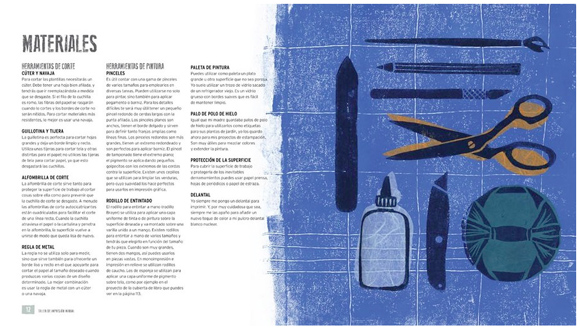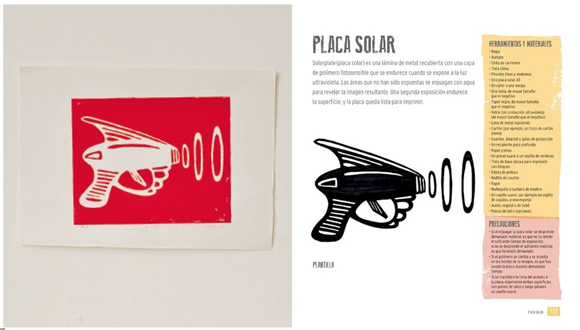
El resurgumiento de la impresión clásica con tipos de plomo o madera (letterpress) es algo que de un tiempo a esta parte hemos podido constatar todos los que nos dedicamos al campo de la comunicación. Muchos clientes piden volver a esta técnica de impresión que devuelve una especie de diseño táctil e imperfecto. Esta técnica de imprimir utilizando figuras en relieve es básicamente sencilla y asumible y no hace falta disponer de grandes medios para experimentar con ella. Asimismo otras técnicas como la serigrafía, o el estarcido también nos pueden proporcionar grandes resultados con una mínima inversión. Es aqui donde el libro Taller de impresión manual. Técnicas, herramientas y proyectos para hacer en casa, nos puede servir perfectamente de guía para comprender que es, como se puede hacer y que podemos conseguir a nivel casero poniendo en práctica los recursos de estas técnicas convertidas en este caso en artesanía.
A través de 23 proyectos entre los que se incluyen la impresión de camisetas, espejos, tarjetas de felicitación o incluso manteles, examinaremos las diferentes técnicas de impresión con todo lujo de detalles, desde las herramientas necesarias hasta los pasos que se han de dar para finalizar el producto. Todos los proyectos son sumamente atractivos y desprenden un acercamiento a una expresión artística muy interesante. Tengo la sensación de que este libro puede proporcionar unas buenas ideas a todo aquel que se quiera introducir en el mundo de la reproducción de imágenes de una forma asequible, creativa y muy divertida.
Taller de impresión manual
Técnicas, herramientas y proyectos para hacer en casa
Vanessa Mooncie